Basic Typography Concepts 字型基礎概念
Alphabet 字母表
字母表是一套簡單的符號系統,每個符號代表一個基本的語音。我們把這些符號叫做字母。字母表和其他寫字的方式不一樣,比如有的文字用符號表示音節,有的用符號表示詞的意思。現在的英語除了字母以外,還會用一些特殊符號,像數字(1、2、3)和符號(@、&)。
Character 字元
字元就像是文字的積木,包括字母、標點符號等基本寫作符號。它和我們實際看到的字的樣子(字形)有關,但不完全一樣。
比如說,同一個字元"A",在不同的字型裡可以有不同的樣子。每個字型都會把字元對應到它自己獨特的顯示樣式。反過來說,有時候不同的字元也可能用同樣的樣子來顯示。你可以把字元理解為抽象的概念,而字形則是我們真正看到的具體樣子。
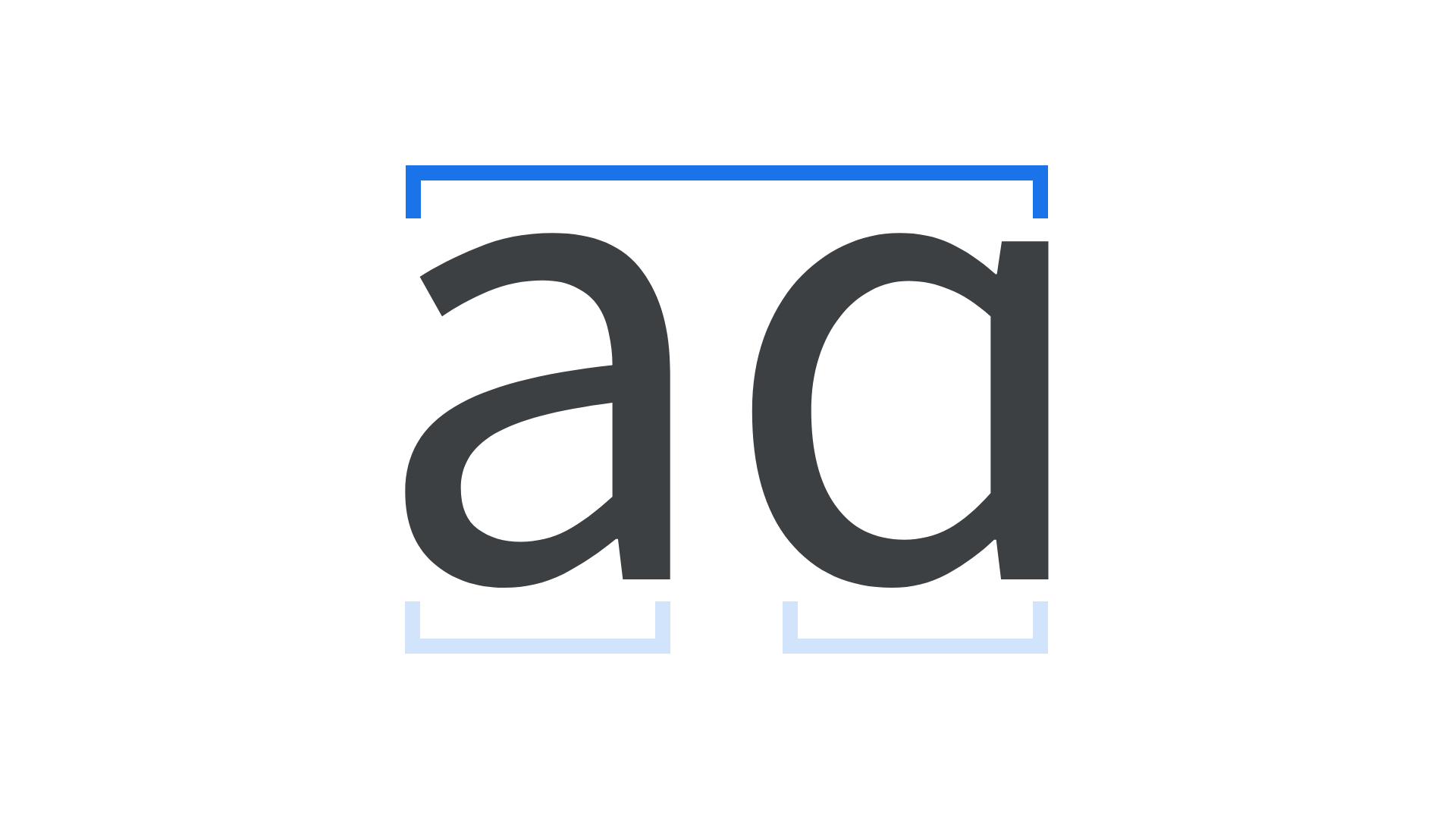
Letters 字母
字母就是用來表示發音的符號,是組成字母表的基本單位。
從語言學角度來說,字母是書寫系統最基本的組成部分,專業上叫做"字位"。在日常生活中,我們說的"字母"主要指英語中的A、B、C這樣的符號。不過要注意的是,像中文這樣用符號來表達意思的文字(比如"雨"、"月"、"人"),我們一般叫它們"字元"而不是"字母"。
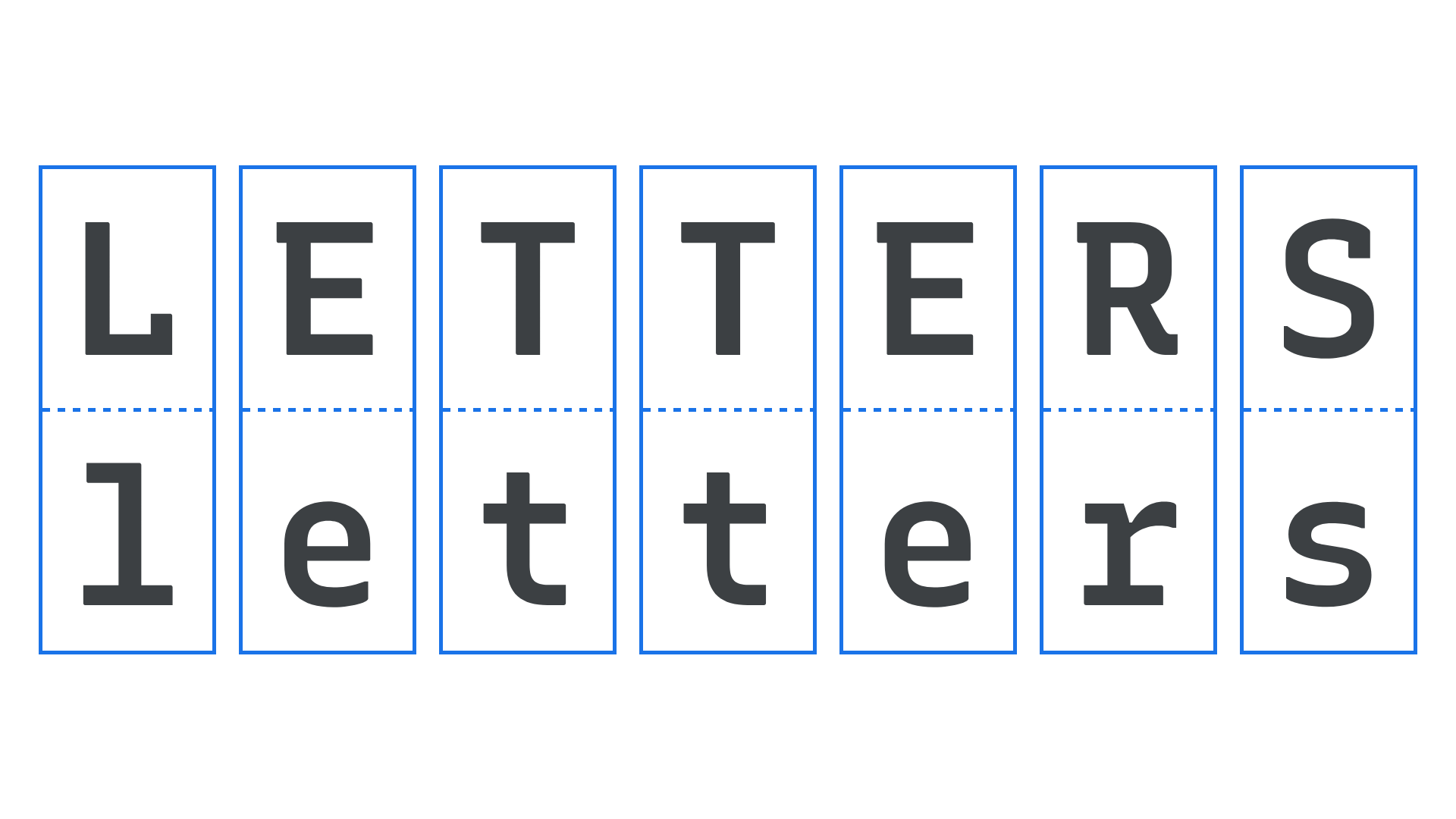
Type 活字
活字就是把文字做成可以重複使用的印刷模具。以前人們只能手寫文字,但有了活字印刷技術後,就可以大量快速地印刷書籍了,這個發明對人類文明的發展有很大影響。
今天我們說的"活字"主要指的是字型的設計方式,包括字的外觀和讓人容易閱讀的設計。比如在Google Fonts裡,你能找到普通的文字字型、特殊裝飾用的字型,還有圖示和表情符號。
Typeface 字型設計
字型其實就是文字的外觀設計。你可以把字型想象成文字的"樣式"或"長相"。
簡單來說,當我們說"字型"時,指的是文字的整體設計風格(比如宋體、黑體),而"字型"則是這個設計的具體檔案形式。就像一首歌可以儲存成MP3檔案一樣,字型設計也需要儲存成字型檔案才能在電腦上使用。
Font 字型
字型(Font) vs 字型設計(Typeface)
字型設計就是文字的整體外觀和風格。比如說,你看到的字是圓潤的還是方正的,這就是字型設計的表現。而字型呢,就是讓你能在電腦上使用這種設計的具體檔案。
舉個簡單的例子:微軟雅黑是一個字型設計,而微軟雅黑的粗體版本就是一個具體的字型。
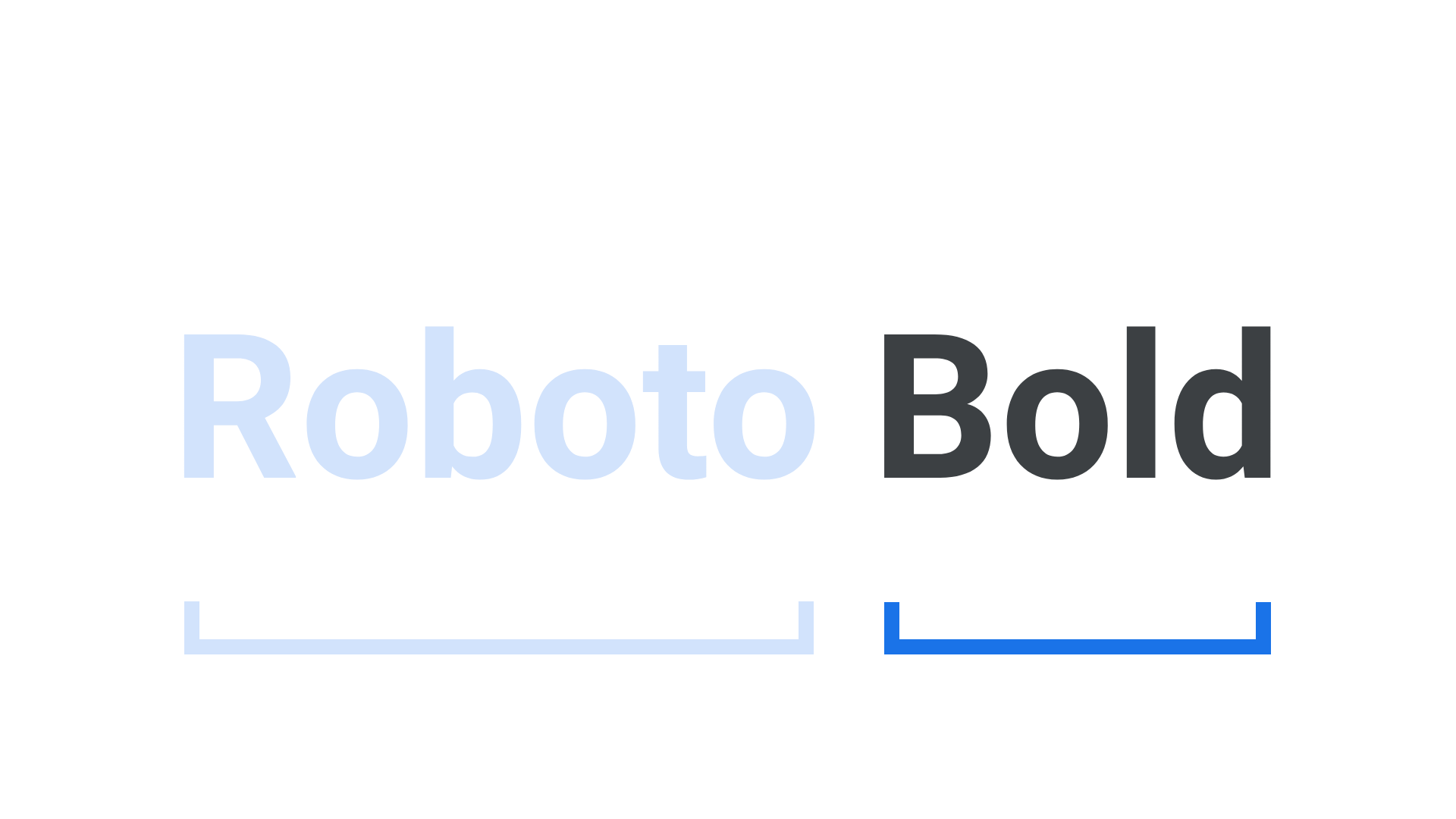
Glyph 字形
字形就是我們實際看到的文字樣子。每種字型都會把抽象的字元轉換成具體的字形顯示出來。每個字形都按照一定的規則(Unicode標準)儲存在字型檔案裡。
字形和字元是有區別的:一個字元可以有不同的顯示樣子(比如同一個"A"可以寫得漂亮一點或簡單一點),而一個字形有時也可以表示多個字元(比如把"fi"合在一起寫)。簡單說,字元是我們腦子裡的概念,而字形是我們眼睛真正看到的樣子。
Script (writing system) 文字系統
文字系統就是一種寫字的方法,它告訴我們怎麼把語言寫下來。每種文字系統都有自己的規則,告訴我們該怎麼正確地寫字。
有趣的是,不同的語言有時會用同一種文字系統。就拿英語、法語、德語、挪威語和葡萄牙語來說,雖然它們說起來完全不一樣,但都用相同的拉丁字母來寫。只是每種語言會在字母上加一些小符號,讓它們能更好地表達自己的發音。
字型示例:EB Garamond,Roboto Slab,Comfortaa,Open Sans,Noto Serif, Noto Sans
其他文字系統包括:希臘文(拉丁文的基礎)、西里爾文(源自希臘大寫字母)、阿拉伯文、韓文、南亞和東南亞的印度文字、漢字,以及非洲的傳統文字。
Unicode 統一碼
Unicode 就像是給每個文字元號都安排了一個獨特的號碼。就算你用不同的語言寫同一個字母(比如"A"),它的號碼都是一樣的,這樣電腦就能準確識別它。
想象一下,就像每個人都有自己的身份證號碼一樣。同一個字母"A"可以寫得好看一點或者簡單一點,就像同一個人可以穿不同的衣服,但身份證號碼(Unicode編號)始終是一樣的。
雖然字型設計師可以隨意決定在字型裡放什麼字元(比如可以只做數字),但一般的字型都會包含我們常用的那些字元。
Readability 可讀性
1 可讀性就是看文字時覺得舒不舒服。這主要取決於三個方面:讀者自己的情況,比如視力好不好、文章寫得怎麼樣、文字排版的樣子,包括用什麼字型
2 為了讓文字更容易讀懂,我們要考慮:內容是不是有意思、寫得簡單還是複雜、用什麼樣的寫作方式、字型看起來舒不舒服
字型設計也很重要,比如字的粗細、字和字之間的距離、字的大小等,都會影響我們讀起來舒不舒服。
Legibility 可辨識度
可辨識度說的是文字看起來有多清楚。簡單地說,就是我們能不能一眼就認出每個字。這跟文字讀起來舒不舒服(可讀性)不太一樣,但會影響我們讀得舒不舒服。
有些字型設計得特別好認,比如它們會把容易混淆的字母和數字設計得不一樣。舉個例子:數字"1"、大寫的"I"和小寫的"l"(1Il),還有"0"、大寫的"O"和小寫的"o"(0Oo),在好的字型裡看起來都不一樣。字型大小、粗細、顏色,以及字和字之間的距離,都會影響我們認字的清楚程度。
要想文字容易讀,就得要容易認。文字太小容易看不清,但單純放大文字不一定能提高可讀性,就像合同裡的小字放大後也不一定容易讀懂。
字間距大小影響文字的辨識度。某些專用字型,如程式碼等寬字型和車牌字型,都經過特別設計以提高辨識度。
Uppercase & lowercase 大小寫字母
一般來說,文字分為大寫和小寫兩種。大寫字母我們主要用在:
- 句子的開頭
- 人名、地名等專有名詞
- 縮寫詞
- 廣告牌等特殊設計場合
其他時候,我們都用小寫字母。
有趣的是,最早的拉丁字母只有大寫。小寫字母是人們寫字時慢慢發展出來的。
如果要用大寫字母排版,尤其是字比較小的時候,建議把字母之間的距離放大一點,這樣更容易看清楚。
Small caps 小型大寫字母
小型大寫字母其實很簡單,就是把大寫字母做得小一點,讓它能和普通小寫字母很好地配合在一起。它比普通大寫字母看起來更舒服,也不會太顯眼。這種字母的高度一般比小寫字母"x"的高度稍微高一點。
什麼時候用小型大寫字母呢?主要是在寫三個或更多字母的大寫文字時。舉個例子:像"US"這麼短的縮寫用普通大寫字母就可以了,但如果是"UNESCO"這樣比較長的縮寫詞,用小型大寫字母會更好。記住,用大寫字母的時候,字母之間要留出適當的空間。
還有一個重要的提醒:不要直接把普通大寫字母縮小來代替小型大寫字母,因為這樣字會變得太細,看起來不好看。應該用專門設計好的小型大寫字母。
All-caps 全大寫字母
全大寫字母就是把所有字母都寫成大寫。不過要注意,大寫字母不太適合用來寫長段文字,因為這樣會讓人不容易看清楚。所以我們通常只在以下情況用全大寫:
- 寫標題的時候
- 想要強調某些內容的時候
當你用小號字型寫全大寫文字時,如果超過2-3個字母,最好在字母之間多留一些空間,這樣會更容易看清楚。
舉個簡單的例子:大號字型寫"QUIET"時,字母間距可以保持正常;但如果用小號字型寫"LOUD",就需要把字母之間的距離放大一點。如果你真的需要在正文裡用大寫字母,建議用小型大寫字母。因為這種字母看起來比較溫和,不會太突出,更容易和其他文字搭配。
Regularor upright常規字型(正體)
"Regular"(常規)很簡單,它有兩個基本含義:第一種是指字型的粗細程度(在CSS程式碼中用數字400表示),第二種是指字型的正常樣式(就是沒有傾斜的字型)。
為了避免混淆,我們最好具體說明是哪種含義,比如說"常規正體"或"常規斜體"。在網頁設計中(CSS),這種普通的字型樣式叫做"normal",程式碼寫法是font-style: normal;。
"Regular"有時候還可以表示字型的寬度。當字型有窄的或寬的變化形式時,一般把普通寬度叫做"normal"(正常)。比如我們會說"常規正常正體"或"粗體窄斜體"。
Italic 斜體
斜體是一種傾斜的字型樣式,主要用來強調文字。它源自於手寫體,與正體形成鮮明對比。
與單純傾斜的字型不同,斜體在結構上更接近手寫體,有其獨特的風格。一些字型的斜體樣式與其正體差異很大,比如Bodoni Moda、IBM Plex Serif和Source Serif 4等字型。
如果字型沒有真正的斜體(或傾斜體),軟體可能會生成"偽斜體"。和偽粗體、偽小型大寫字母一樣,應該避免使用偽斜體。
Oblique 傾斜體
傾斜體就是把正常的字型往一邊傾斜了一下。這和斜體不一樣,因為斜體是根據手寫字的樣子專門設計的。當我們製作傾斜體時,設計師會細心調整每個字的形狀,確保字型看起來均勻好看,不會出現變形或者有的地方太粗有的地方太細的問題。
傾斜體不像斜體那麼常見,比如Josefin Sans.這樣的無襯線字型
Bold 粗體
粗體就是比普通字型更粗的字型樣式,我們經常用它來讓某些文字顯得更突出、更重要。
粗體到底有多粗?這要看字型設計師怎麼設計。一般來說,粗體的粗細在正常字型和超粗字型之間。現在有些新型字型還可以讓你自己調整字型的粗細。如果你做網頁設計,在CSS程式碼裡用700這個數字就能設定粗體。
Letterform 字形
字形就是每個字母的外觀樣子。同一種字型裡的所有字母都會有相似的設計特點,讓它們看起來是一家人。要了解一個字形,我們會看它的基本組成:比如字母有什麼弧度,是不是中空的,筆畫怎麼寫,以及整體的大小比例(包括小寫字母x的高度,大寫字母的高度,還有字母向上下延伸的部分)。
Terminal 筆畫末端
在字型設計中,筆畫末端就是字母或文字筆畫的結尾部分。簡單來說,就是每個筆畫寫完時的那個收筆地方。
筆畫末端可以有不同的樣子。比如說:大寫字母"E"的橫線兩端可以有裝飾(襯線)、小寫字母"a"的末端可以是圓圓的、有些末端可以比筆畫本身更寬。這些不同的末端設計會讓字型看起來有不同的風格,也會影響我們讀字的時候有多容易看清楚。
Text 正文與文案
正文指的是頁面上的主要文字內容,和標題、說明文字、引用等不一樣。"text"這個詞有時候也用來說明文字的大小,通常指比較小的字號,和"正文"是一個意思。
我們看到的所有文字都需要用字型來顯示,不管是在紙上還是在電腦螢幕上。這些需要排版的文字內容,專業人員通常叫它"文案"。
正文的字號一般會比較小,因為這是我們要長時間閱讀的主要內容。所以正文字型一定要容易看清楚,不能讓人眼睛累。
有些圖示隨著時間變得越來越簡單。比如"儲存"功能現在還在用軟盤的圖示,雖然很多人可能都沒見過真正的軟盤。還有三條橫線的符號,現在大家都知道點它就能開啟選單。
在Google Fonts裡,你能找到這兩種型別的圖示供你使用。
Logo, logomark, logotype Logo、圖形標誌與文字標誌
標誌(Logo)就是一個品牌獨特的標識,通常包含圖案和文字。它讓人一眼就能認出這個品牌。
來看幾個例子:
- 完整標誌:用特製的Anybody字型做成的圖案和文字組合
- 單獨的圖案標誌:最適合放在社交媒體頭像上
- 純文字標誌:在不需要圖案的地方使用,文字都是特別設計過的
圖形標誌(Logomark)就是品牌的圖案部分。比如大家都認識的耐克的勾、星巴克的美人魚,還有蘋果的蘋果圖案。
文字標誌(Logotype)是經過設計的品牌名稱。可能只是調整了字間距,也可能把字母完全重新設計過。
這兩個部分加在一起就是完整的標誌。不過我們平常說"Logo"的時候,也可能指其中任何一個部分。